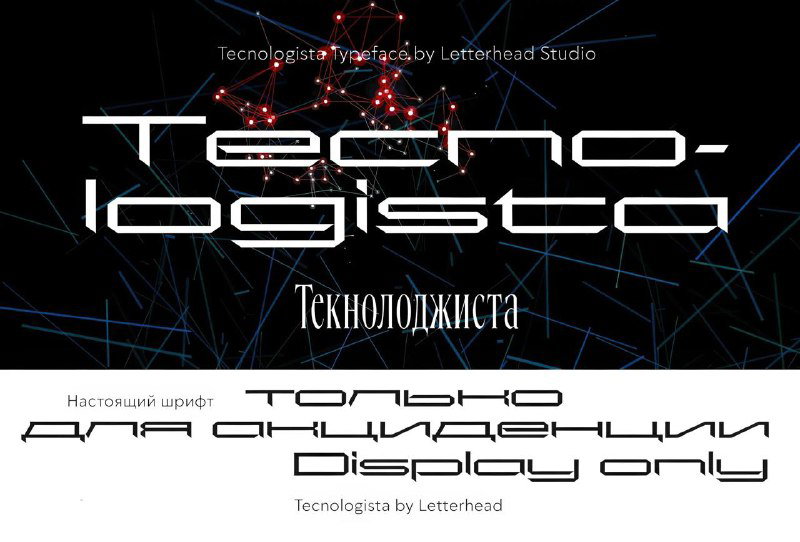
Суперширокий декоративный шрифт с футуристичным обликом. Хорошо подойдёт для плакатов. Включает строчные и прописные знаки латиницы и русского языка, цифры и прочие знаки.